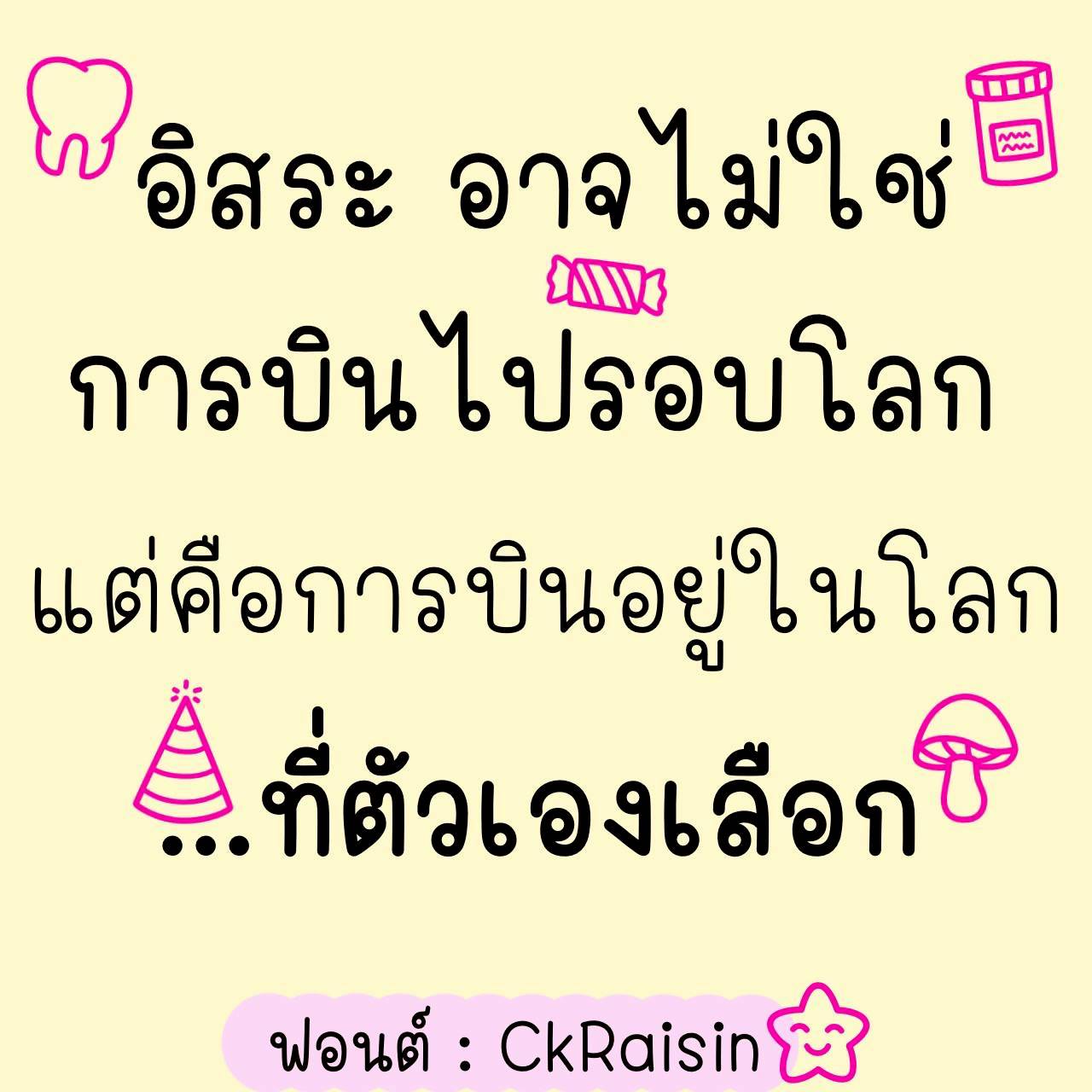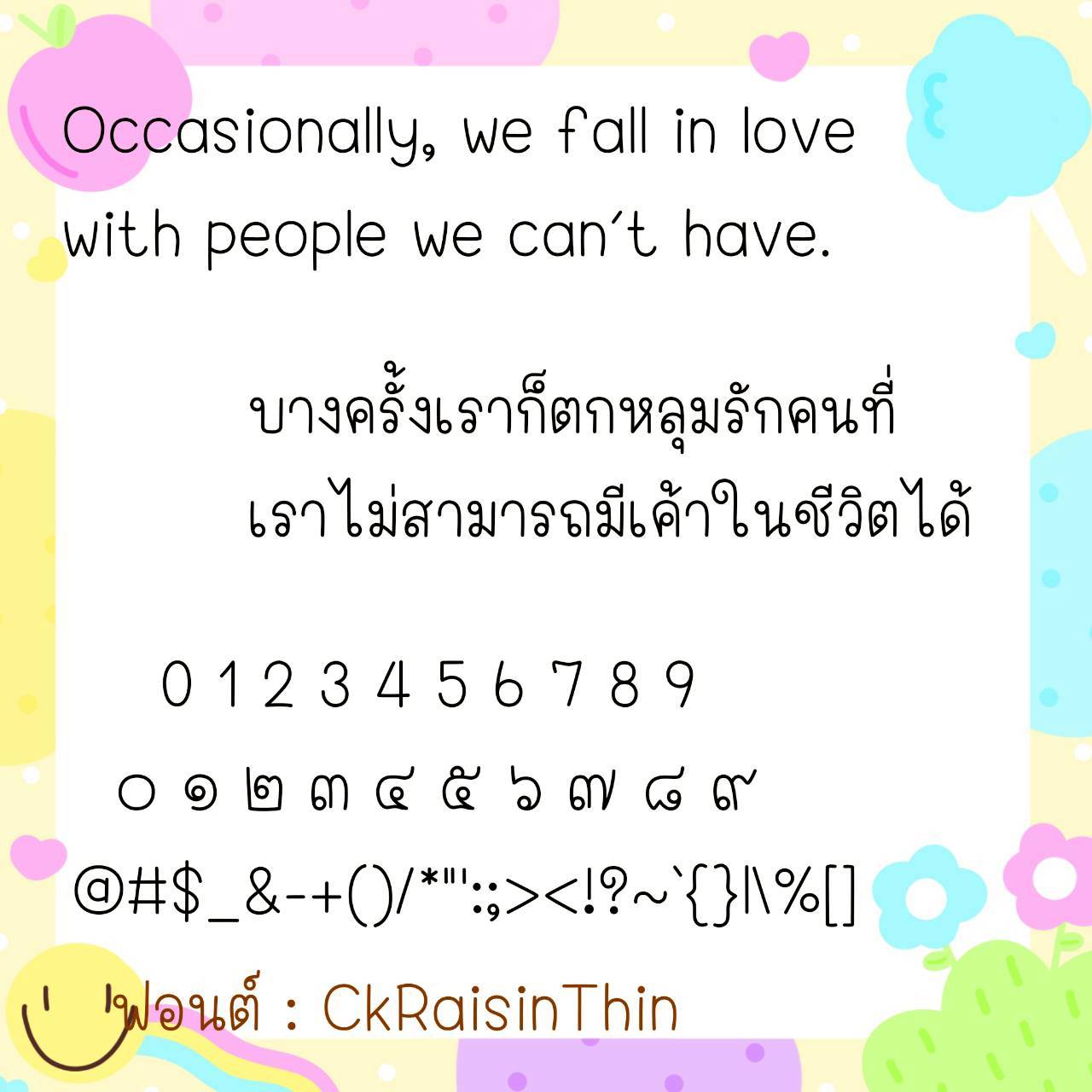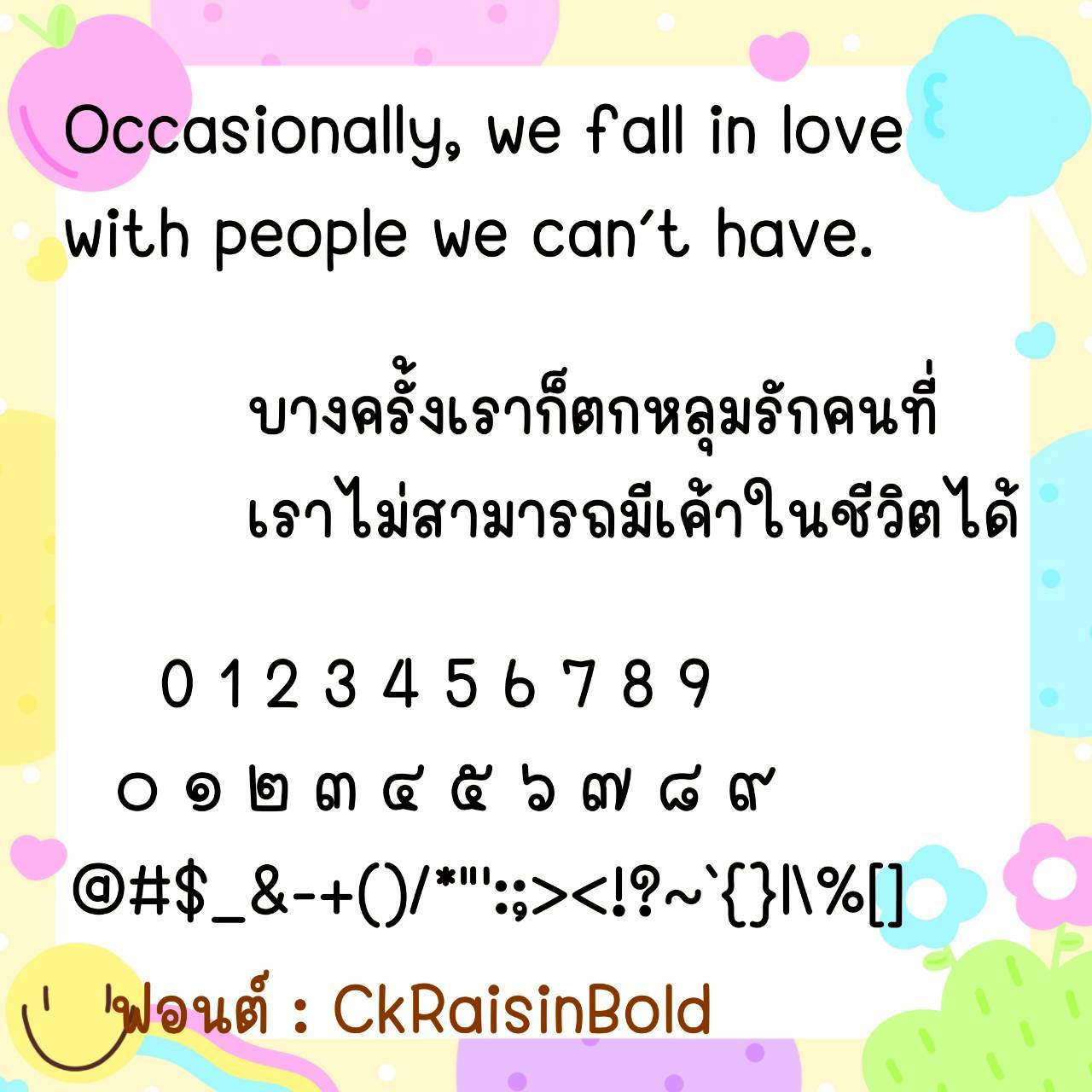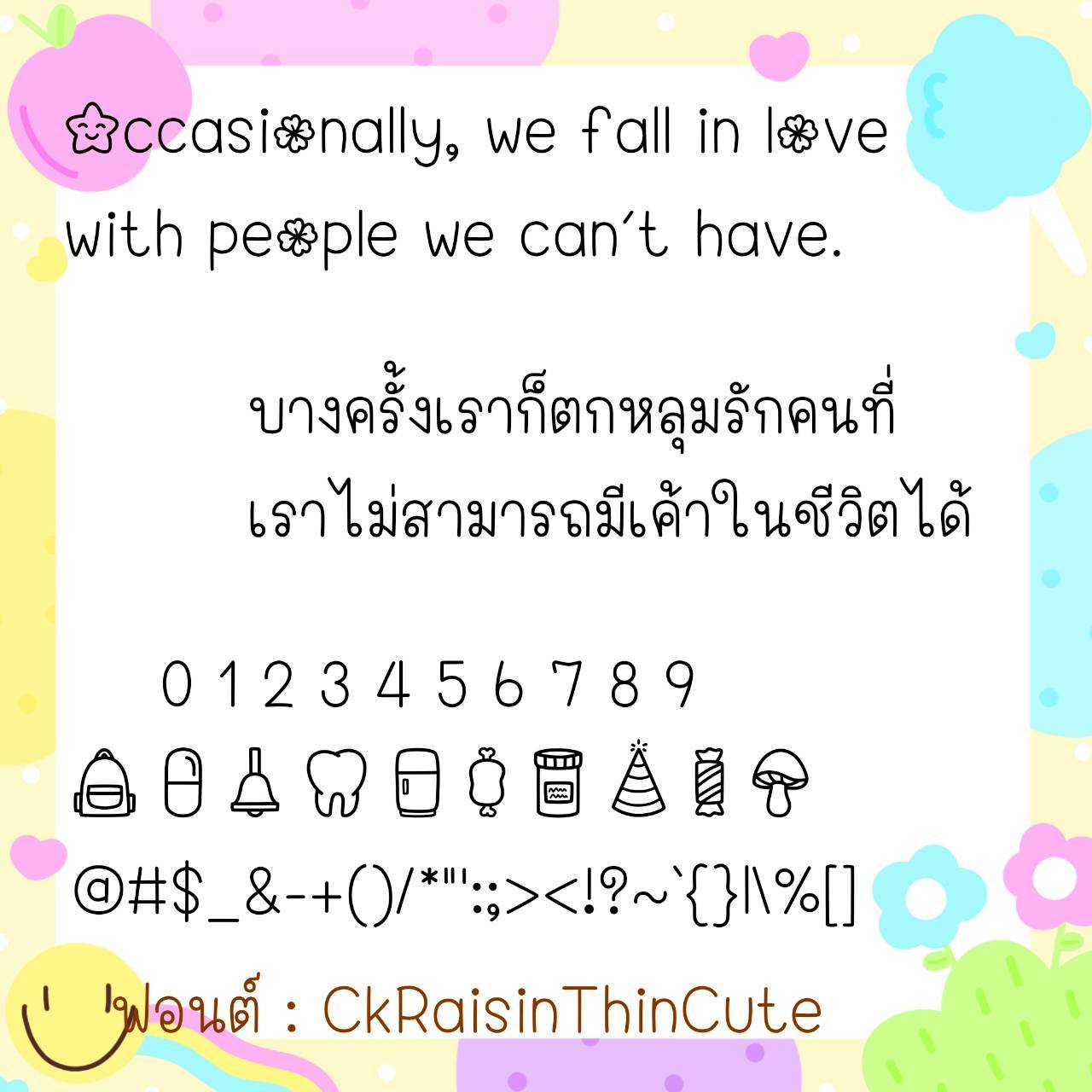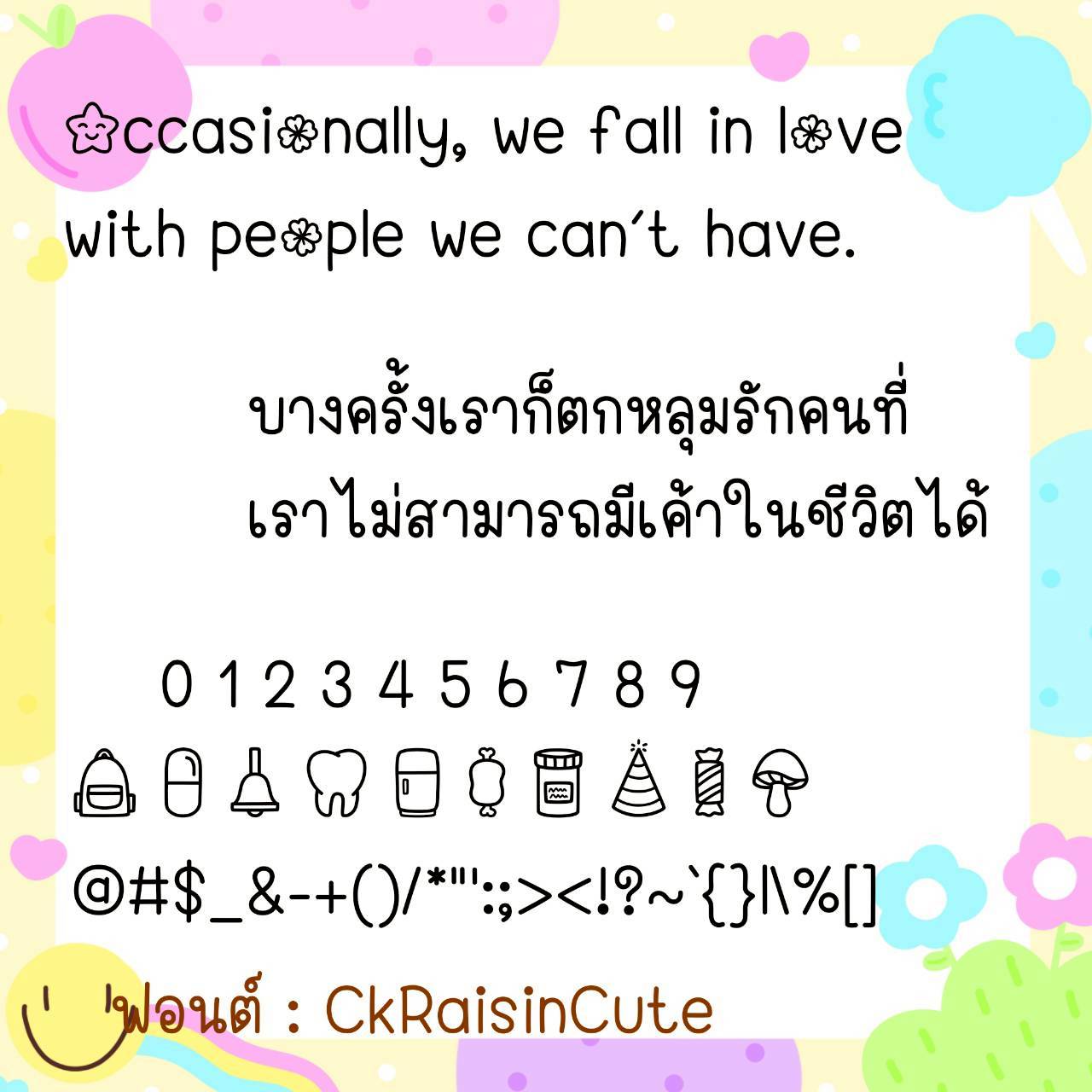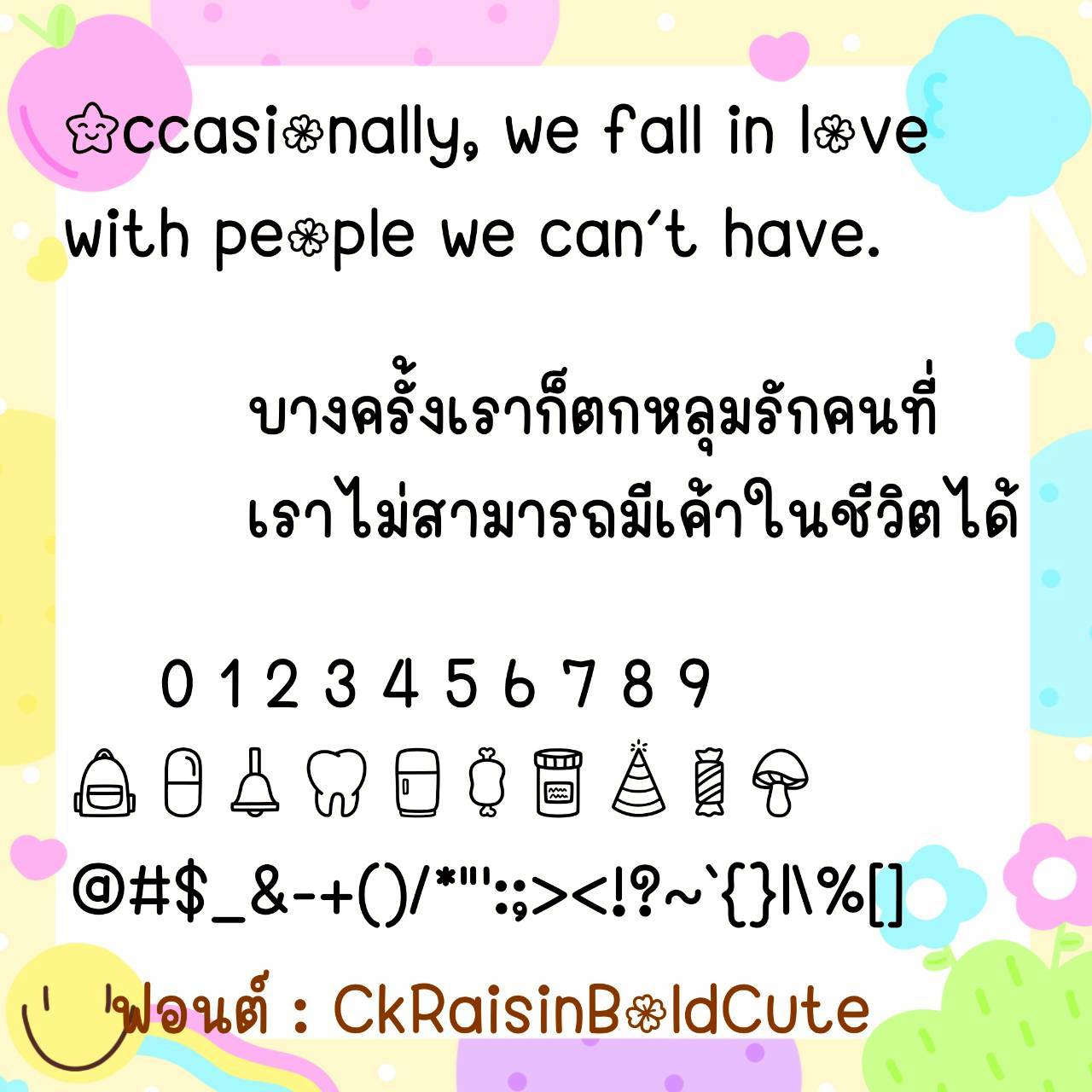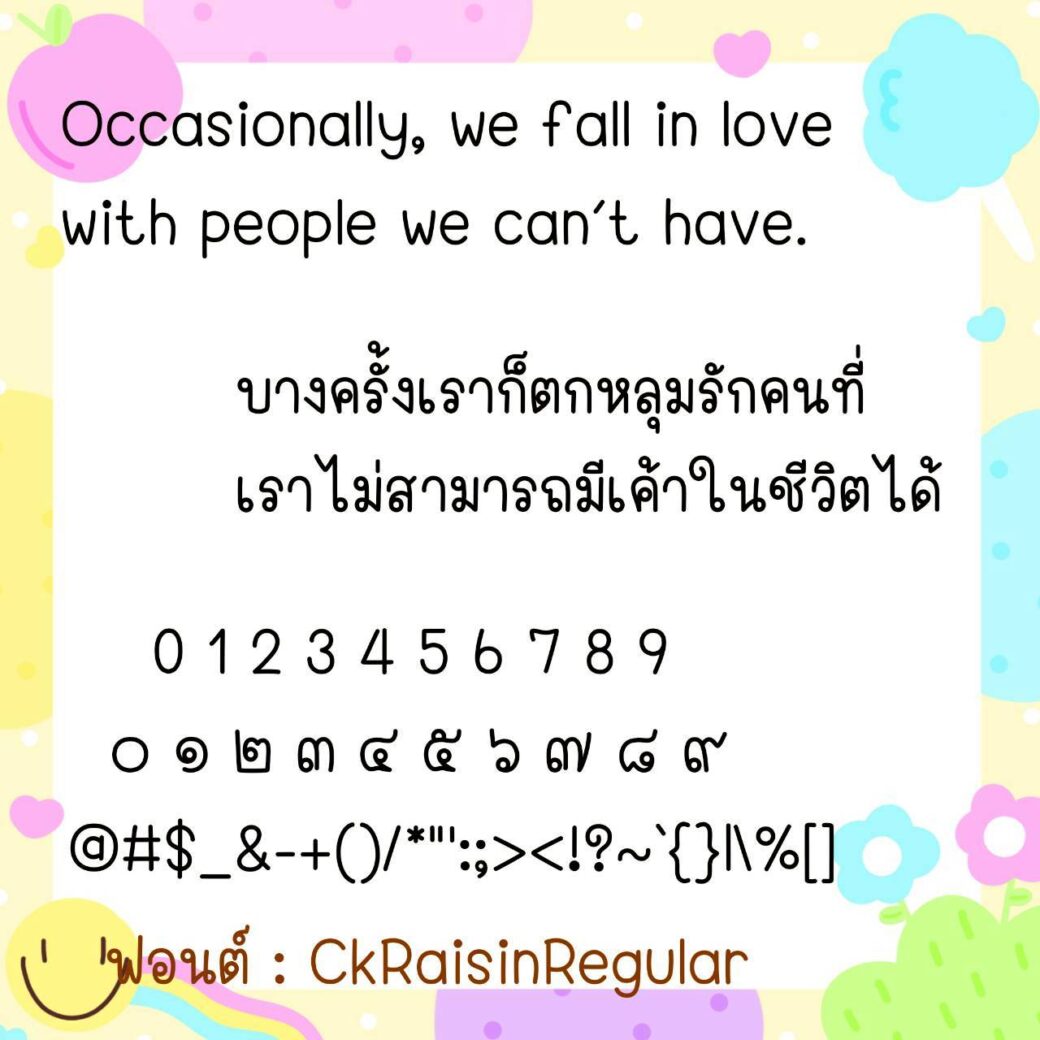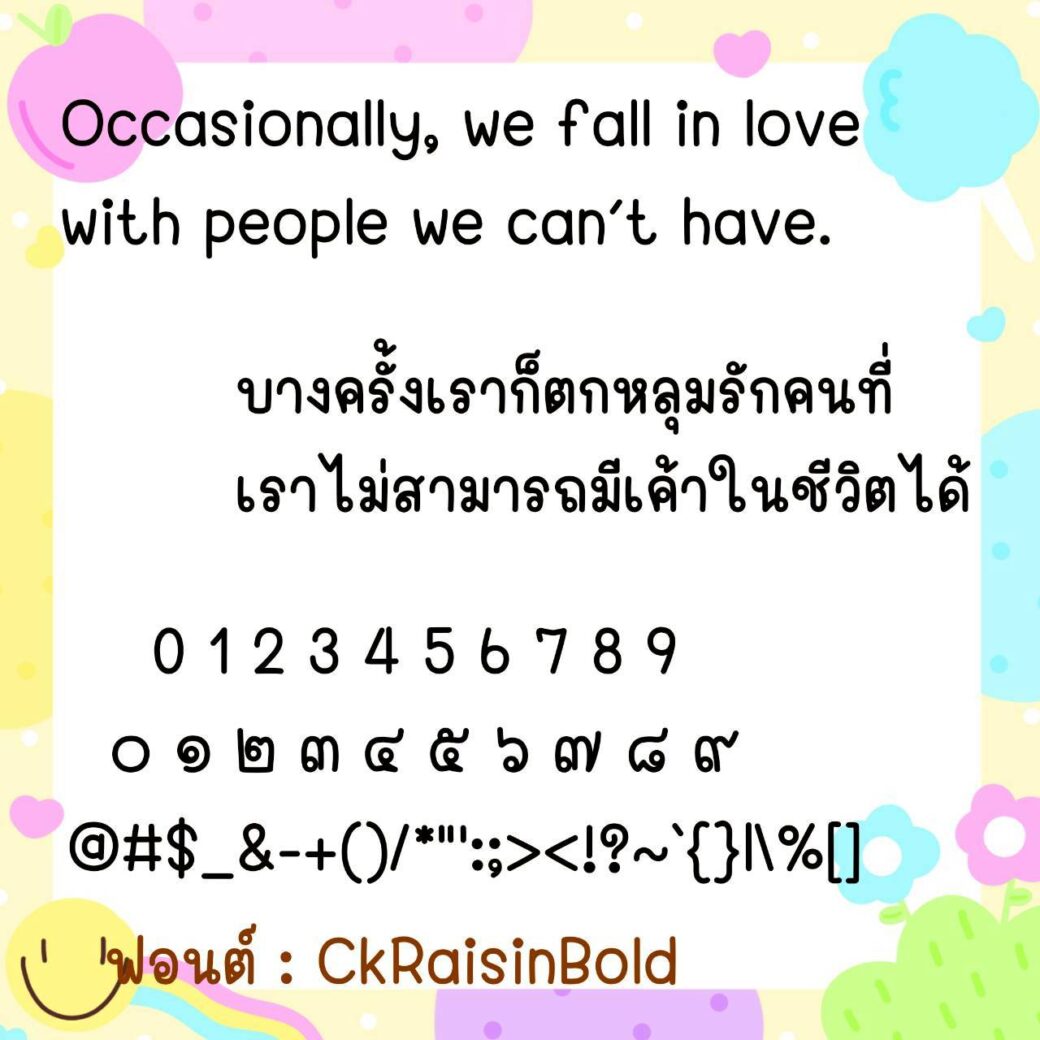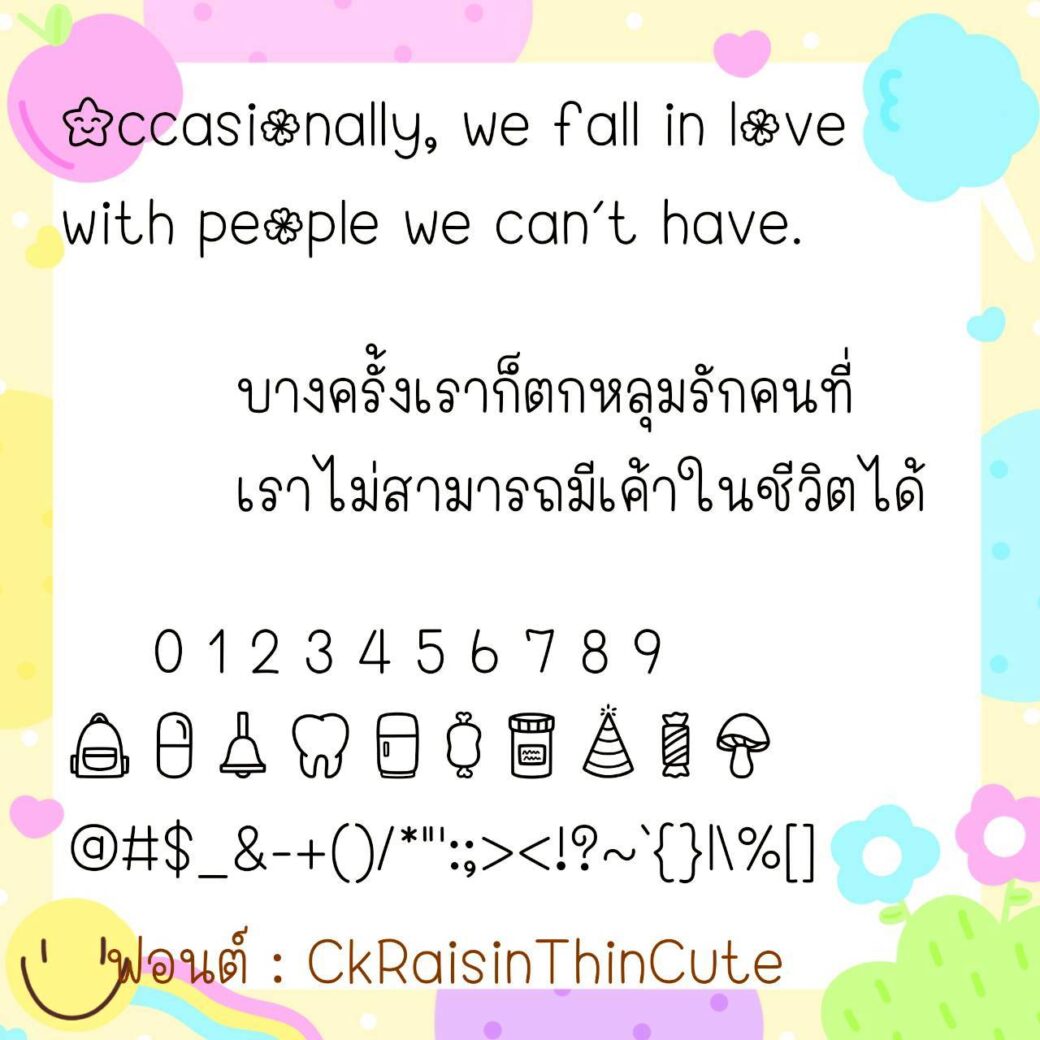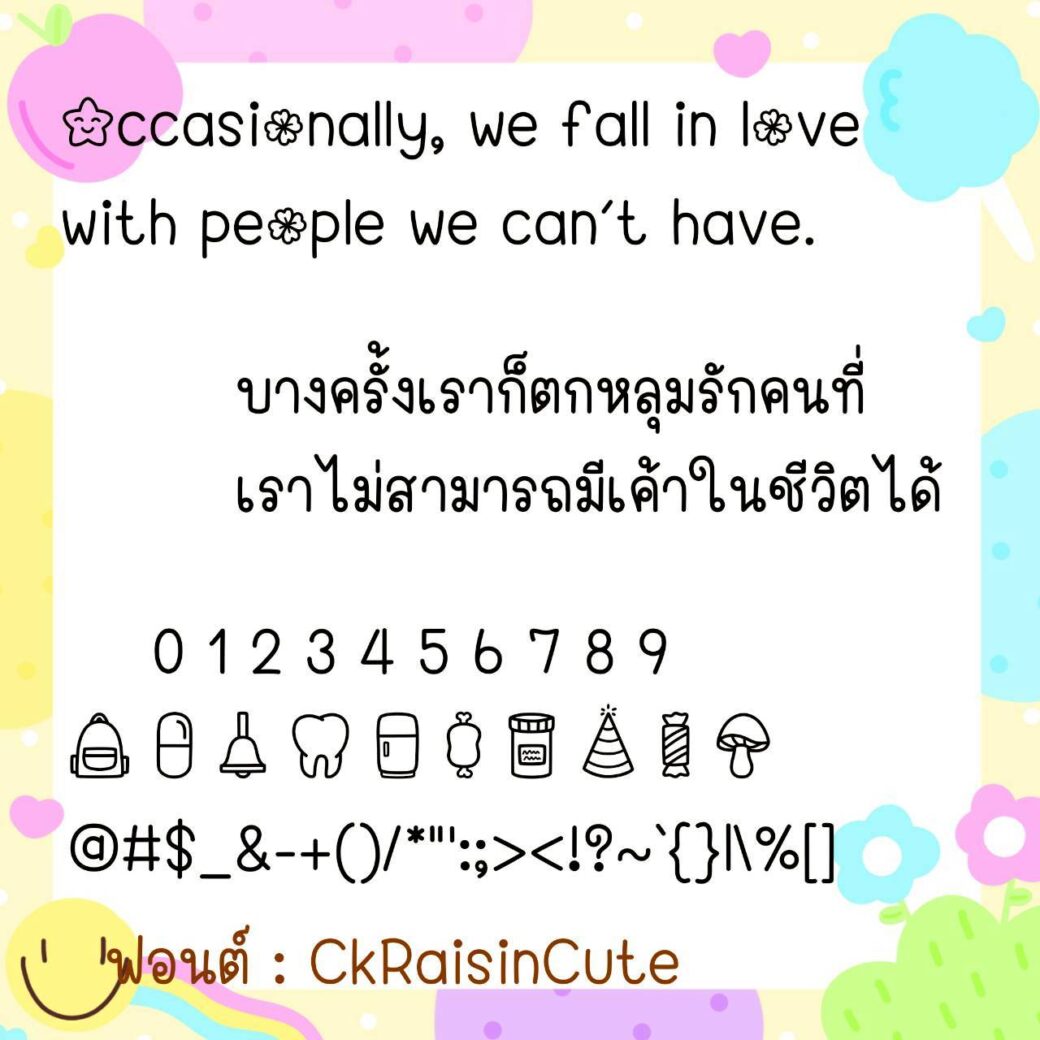
Font CkRaisin
ชื่อสินค้า : Font CkRaisin 💙
🔸 ฟอนต์ลายมือแนวน่ารักกลมมน ขนาดตัวพอดีๆ ใช้งานได้หลากหลาย อ่านง่ายสบายตา และยังมีไฟล์อิโมจิน่ารักๆ ที่ใช้แทนเลขไทยให้ด้วยค่ะ 🥰💙
🔹 This cute, rounded handwriting font is just the right size for a variety of uses. It’s easy to read and easy on the eyes. It also includes cute emoji files that can be used in place of Thai numerals. 🥰💙